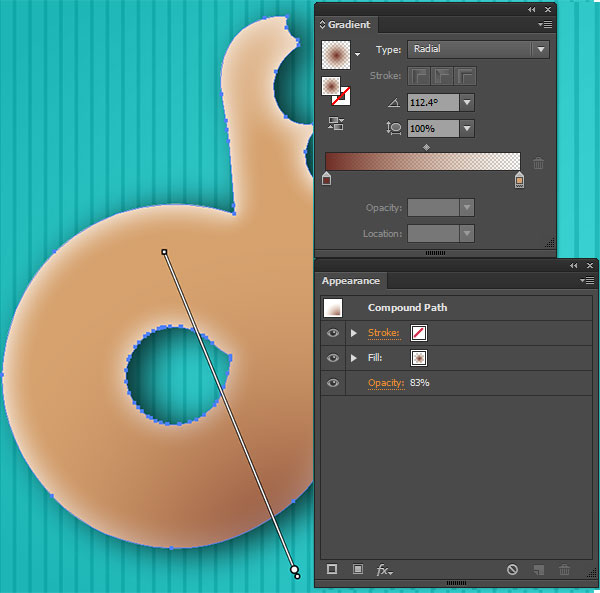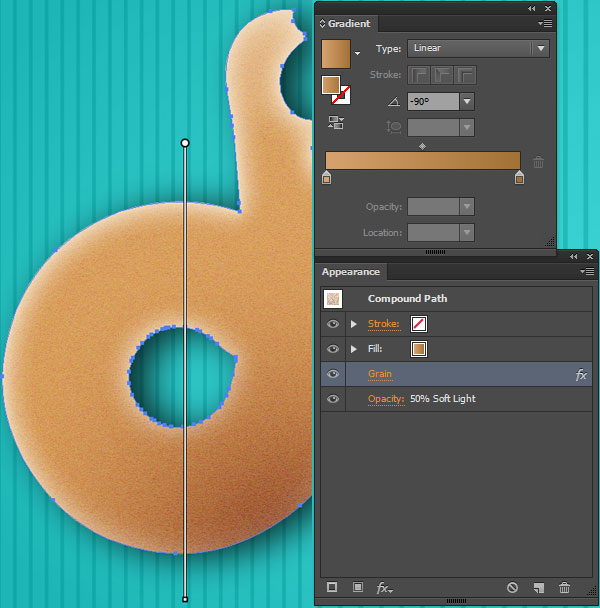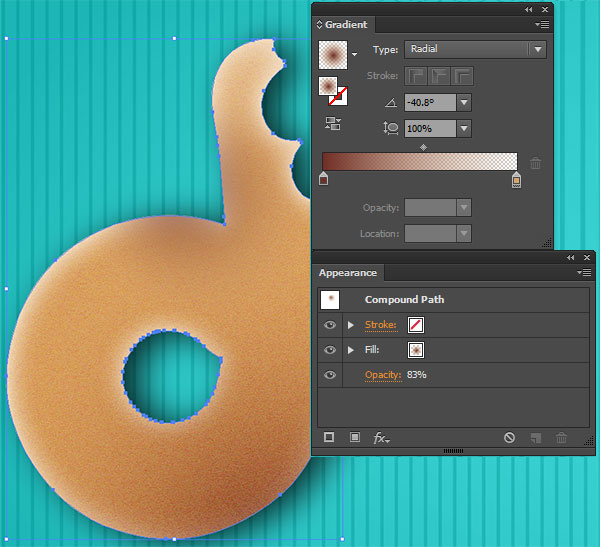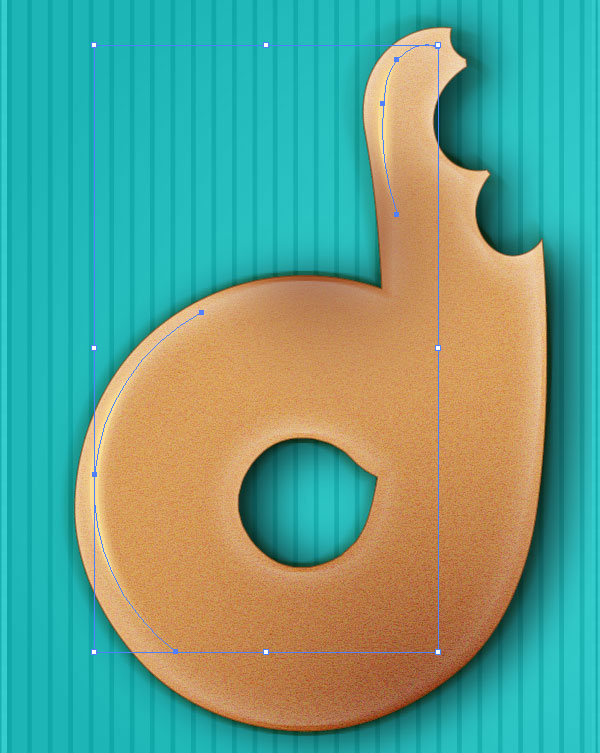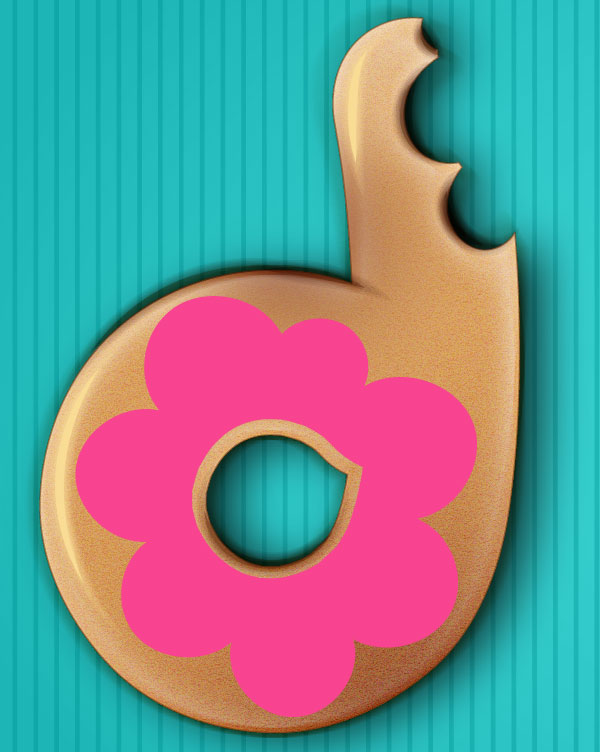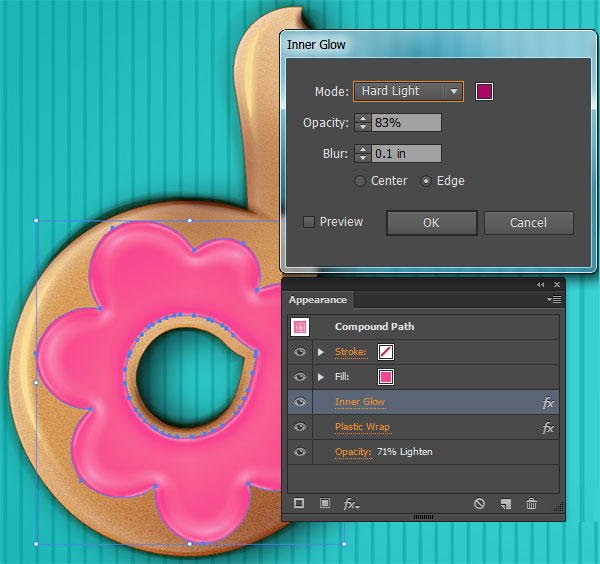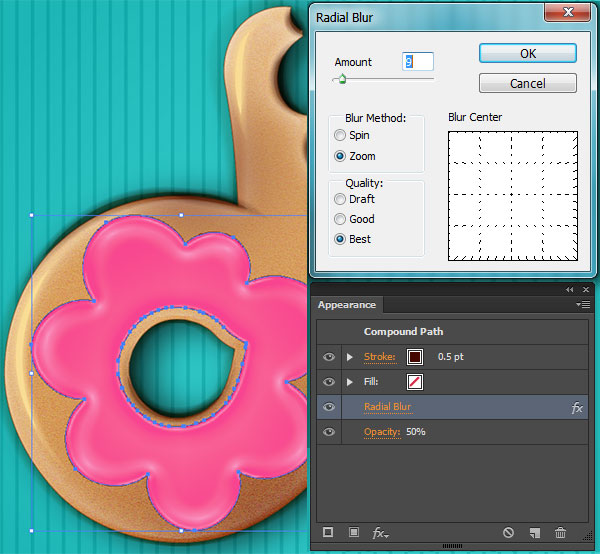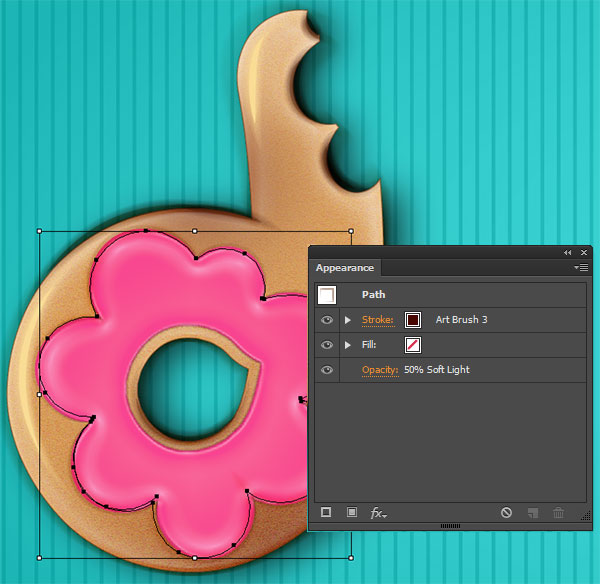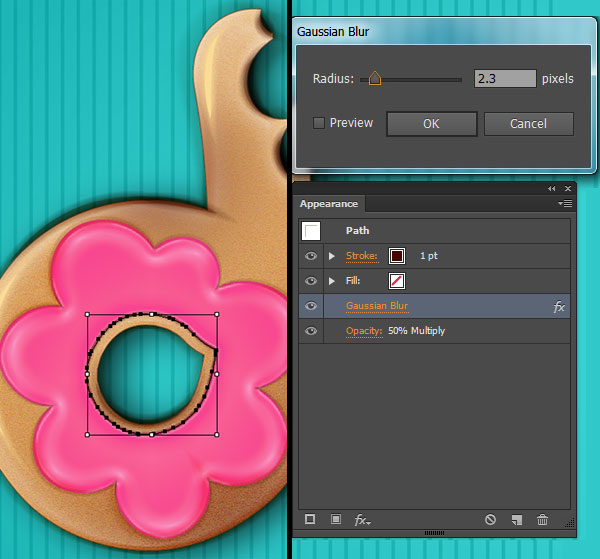
Рисуем пончиковый текст в Adobe Illustrator
В этом уроке мы будем рисовать текст из пончиков в Adobe Illustrator. Мы будем работать с градиентами, векторными и растровыми эффектами, режимами наложения и создадим свои кисти. Вы сможете поэкспериментировать с различными цветами и формами. А еще создание такого типографического эффекта наверняка разогреет аппетит.
Результат
Шаг 1
Создайте новый документ горизонтального расположения. Инструментом Rectangle/Прямоугольник (M) создайте фигуру большую, чем рабочая область. Укажите ей розовый цвет заливки. Инструментом Line Segment/Отрезок линии создайте ровную вертикальную линию слева от прямоугольника. Дублируйте линию и расположите копию справа от прямоугольника. Инструментом Blend/Переход (W) создайте переход между двумя линиями, выбрав  125 Steps/Шагов. Уменьшите Transparency/Прозрачность для этой группы до 79%, и смените Blend Mode/Режим наложения на Soft Light/Мягкий свет.
Шаг 2
Выделите прямоугольник, который создали в самом начале. Инструментом Gradient Tool/Градиент (G) залейте его радиальным градиентом от розового к темно-розовому. Вы можете выбрать другие цвета, главное следите чтобы темный цвет был у краев, а светлый — посредине.
Шаг 3
В случае если вы решите изменить цвет фона, нарисуйте другой прямоугольник поверх всего и смените его режим наложения (Blend Mode) на Color/Цвет.
Шаг 4
Нарисуем буквы. Используя инструмент Pencil/Карандаш (N) аккуратно рисуйте простые округлые буквы. Чтобы рисовать более плавные линии настройте опцию Fidelity/Точность. Для этого нажмите Enter, когда выбран инструмент Pencil/Карандаш, и в появившемся окне, перетяните бегунок опции Fidelity/Точность вправо. Укажите Stroke Weight/Толщину обводки в 12-20 pt. Используйте бежевый, коричневый или желтый цвет для ваших букв. В палитре Strokes/Обводка  выберите округлые Caps/Концы и Corners/Углы.
Шаг 5
Нарисуйте буквы и выровняйте их по нижнему краю. Для этого выделите все буквы и в палитре Align/Выравнивание нажмите на соответствующую иконку. Разберите буквы, вы брав в меню Object > Expand/Объект>Разобрать.
Шаг 6
Инструментом Pencil/Карандаш или Pen/Перо(P), нарисуйте фигуру, откусывающую часть от пончика. Сделайте это для букв O, D, и T. Следите чтобы контур был закрытым. Выделяя созданную фигуру и букву, в палитре Pathfinder/Обработка контура нажимайте на Minus Front/Минус верхний.
Шаг 7
Используя светлый цвет (в нашем случае розовый) нарисуйте глазурь, как показано на картинке ниже. Чтобы убрать дырку в букве «D», выделите букву и глазурь, инструментом Shape Builder/Создание фигур (Shift-M) выделите дырку. Снимите выделение и удалите дырку. Вот что должно получиться. Посмотрите также на откусанные кусочки.
Шаг 8
Займемся оформлением первой буквы. Дублируйте ее (Ctrl+C > Ctrl+F). Укажите копии отсутствие заливки и светло-коричневую обводку толщиной в 3pt. Смените Blend Mode/Режим наложения для этой фигуры на Soft Light/Мягкий свет.
Шаг 9
Вновь дублируйте слой с буквой «D», укажите отсутствие заливки и обводку светло-коричневого цвета толщиной в 0.5pt. Blend Mode/Режим наложение укажите Normal/Нормальный.
Шаг 10
Чтобы было удобнее работать с булочной частью буквы-пончика, можете скрыть (Ctrl+3) глазурь. Выделите букву «D», дублируйте ее и в меню выберите Effect > Stylize > Inner Glow/Эффект>Стилизация>Внутреннее свечение. Укажите настройки как показано ниже.
Шаг 11
Теперь укажите букве тень: Effect > Stylize > Drop Shadow/Эффект>Стилизация>Тень. Настройте параметры как показано ниже.
Шаг 12
Вновь дублируйте слой буквы и используя Gradient/Градиент укажите букве радиальный градиент как показано ниже.
Шаг 13
Вновь дублируйте букву. Укажите Blend Mode/Режим наложения Color Burn/Затемнение основы, Opacity/Непрозрачность в 53% в палитре Transparency/Прозрачность. В меню выберите Effect > Sketch > Note Paper/Эффект>Эскиз>Почтовая бумага. Настройте эффект как показано ниже.
Шаг 14
Еще раз дублируйте букву и примените к ней линейный градиент как показано ниже. Укажите букве Opacity/Непрозрачность в 50% и Blend Mode/Режим наложения Soft Light/Мягкий свет.
Добавим зернистости: Effect > Texture > Grain/Эффект>Текстура>Зерно. Настройте как показано ниже.
Шаг 15
Еще раз дублируйте букву и укажите ей радиальный градиент как показано ниже. Этот тот же градиент, что и в 12 шаге, разница в том, что на этот раз он должен идти от левой верхней части.
Шаг 16
Для создания деталей, мы нарисуем две кисти. Процесс их создания тот же, отличаются они лишь цветом. Одна кисть — кремового цвета, вторая — коричневая.
Инструментом Ellipse/Эллипс(L) нарисуйте сплющенный овал. Инструментом Convert Anchor Point/Преобразовать опорную точку (Shift-C) кликните по левой и правой точке, чтобы убрать округлость углов.  Выделив овал, в меню выберите Object > Path > Offset Path/Объект>Контур>Создать параллельный контур. Укажите отступ в -8px. Выделите больший овал и укажите ему непрозрачность в 0%. Выделите оба овала и укажите им переход (при помощи инструмента Blend/Переход) в 6-10 шагов.
К сожалению, конкретные цвета в оригинальном уроке не указаны. Вы можете подобрать их на глаз или же определить при помощи пипетки с существующих скриншотов.